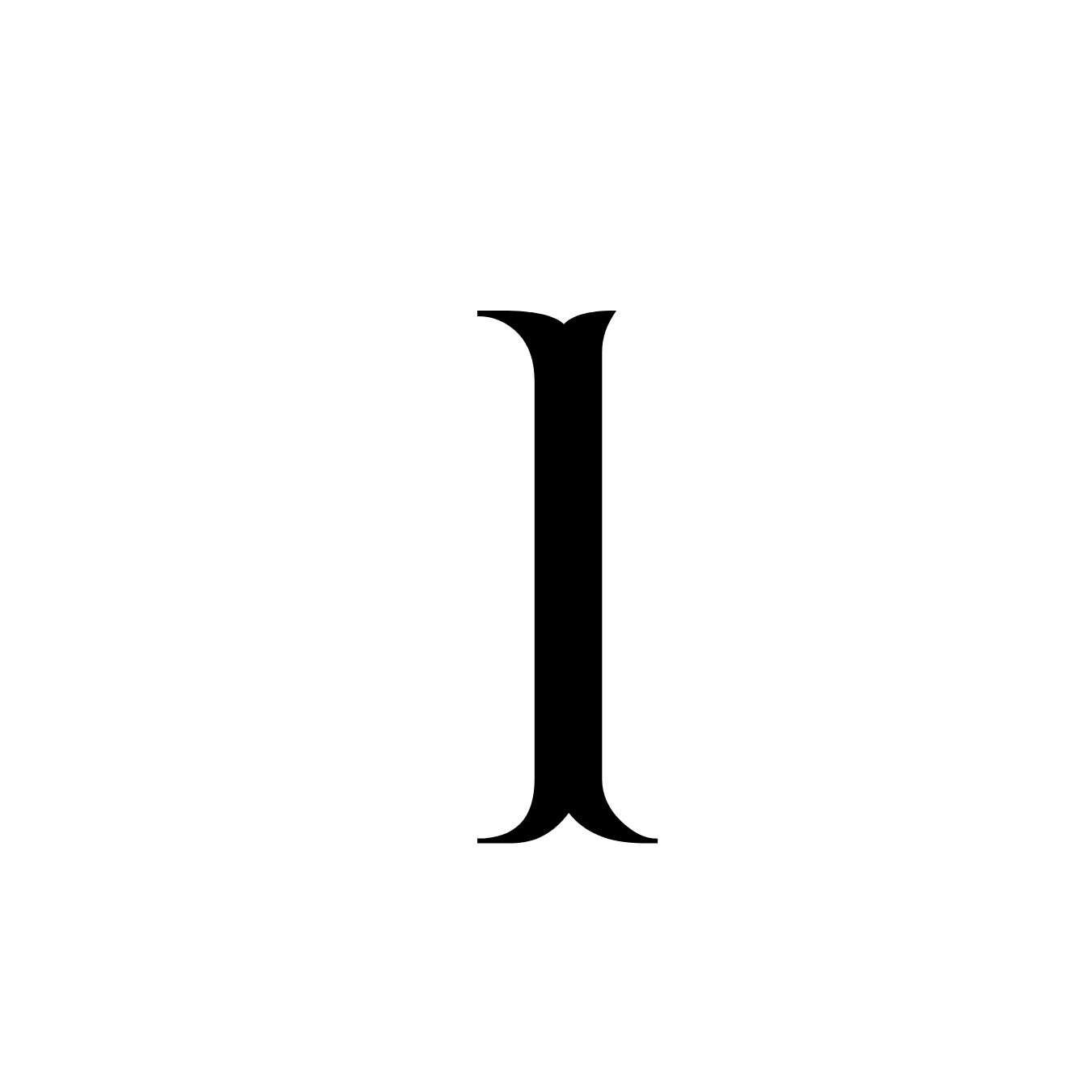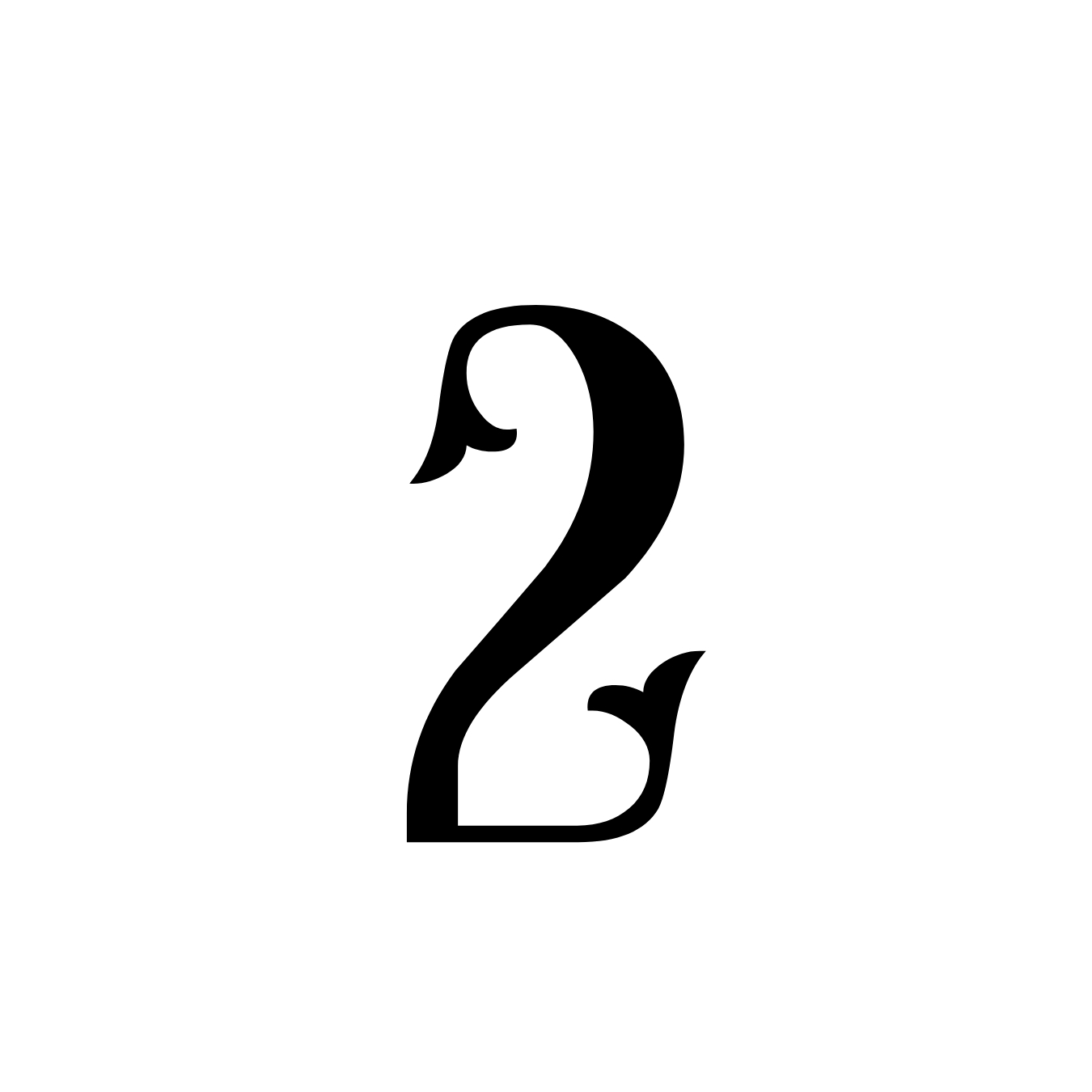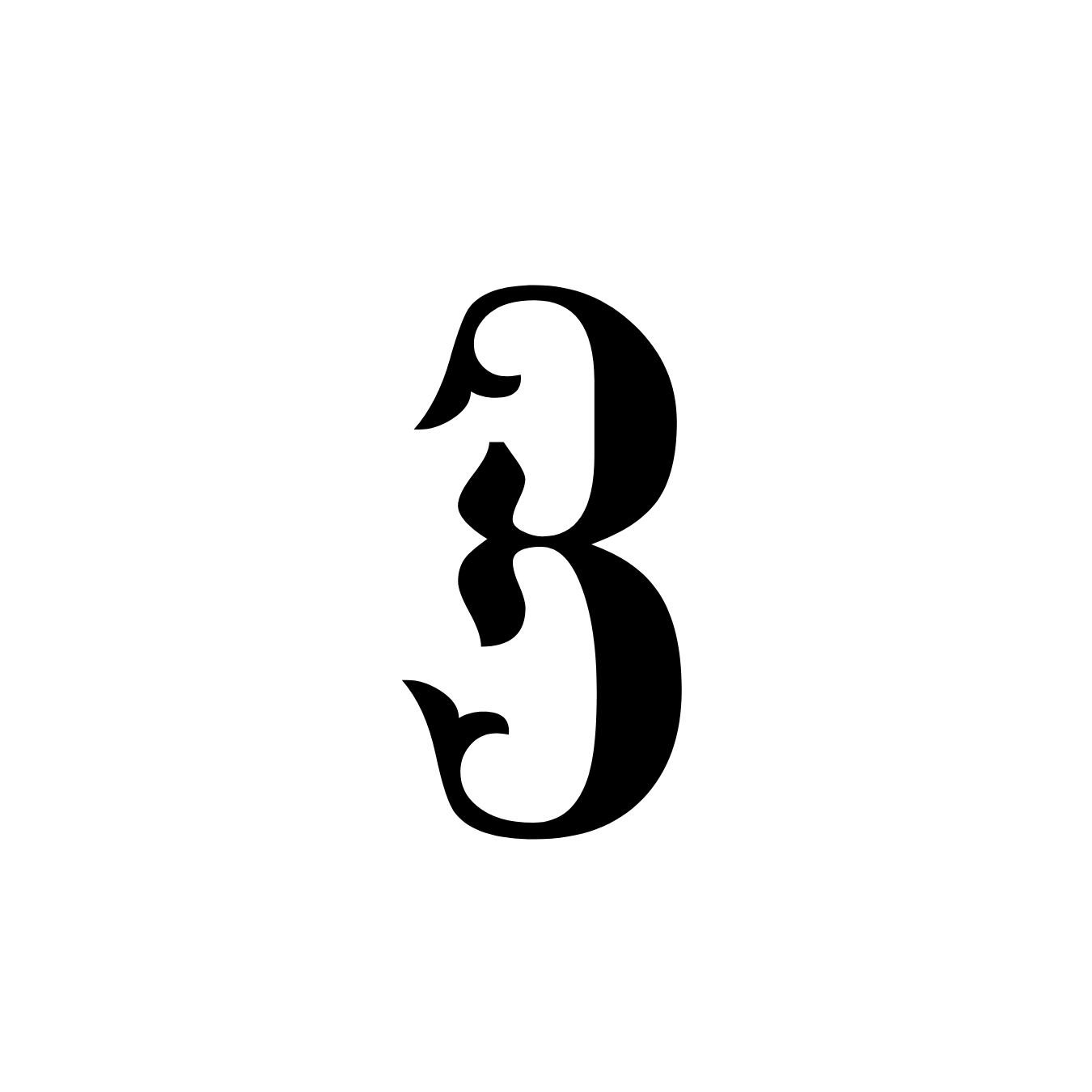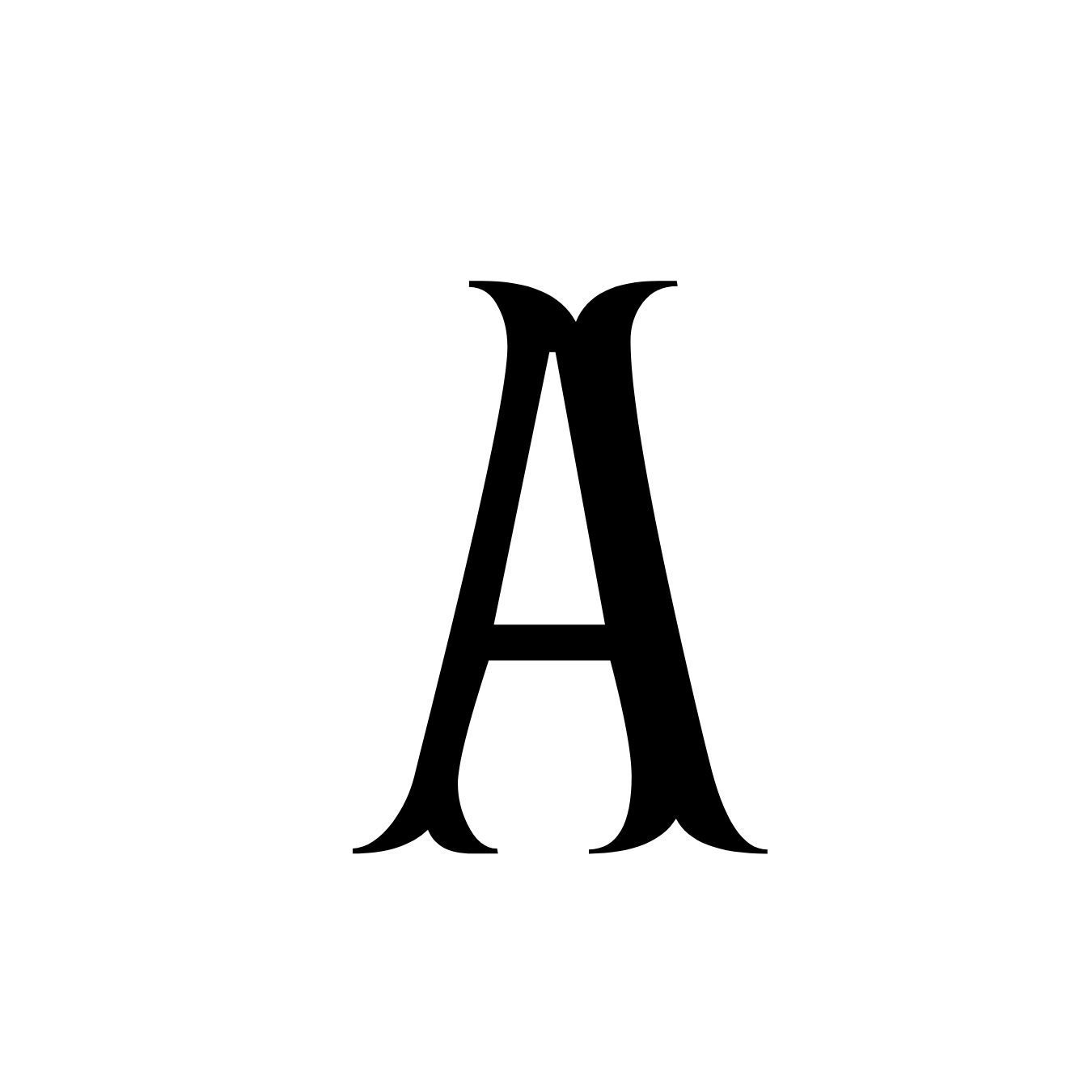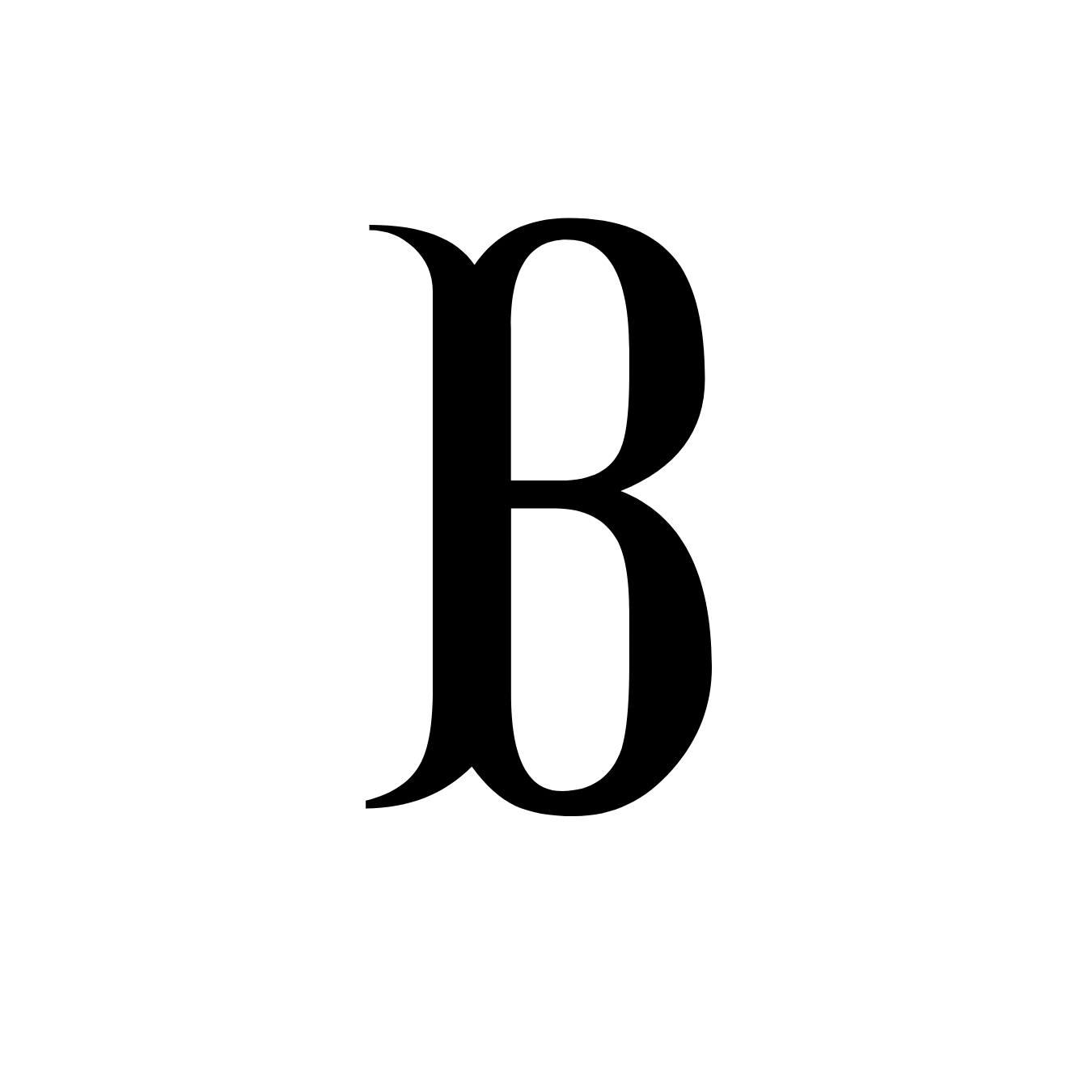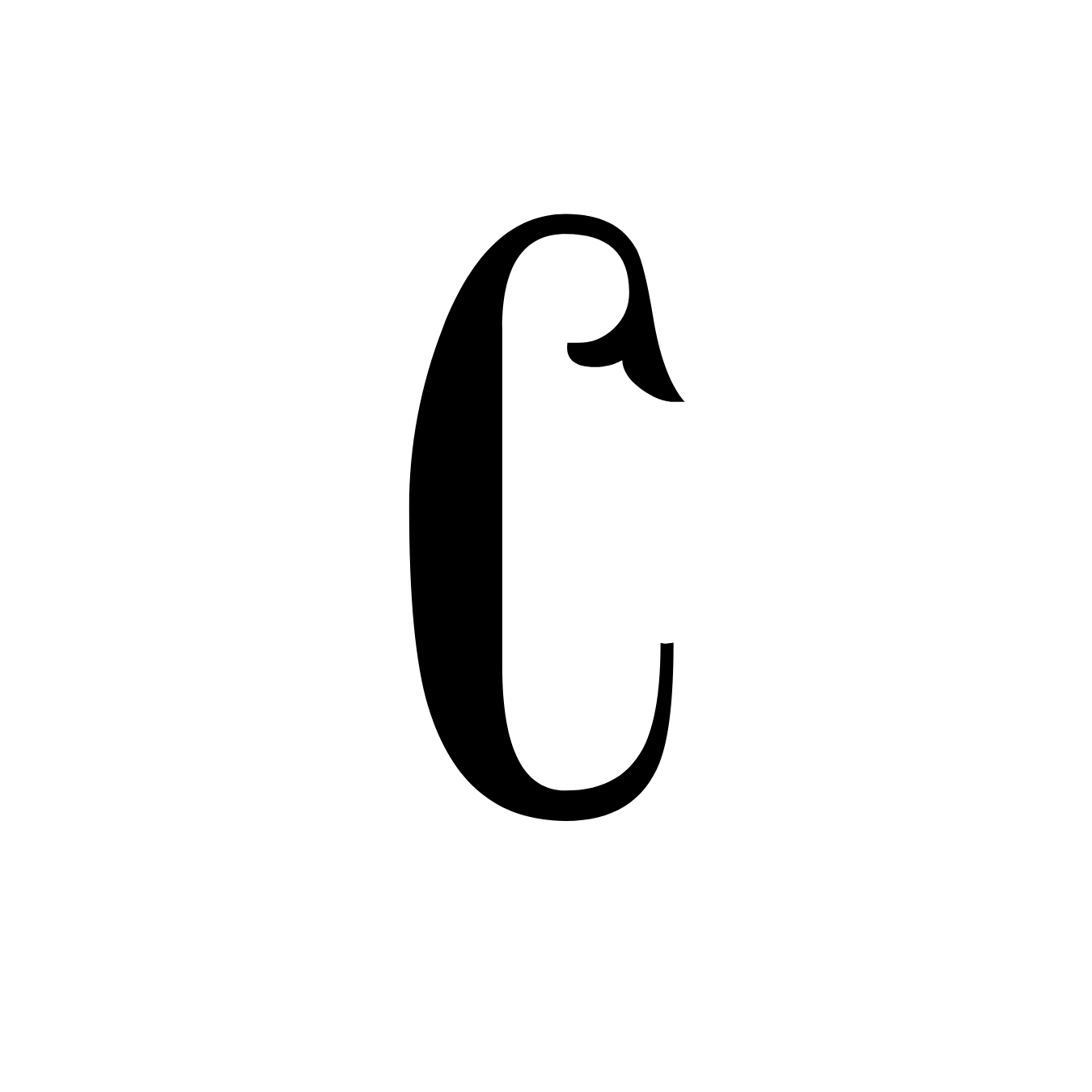
Mermaid Monogramm Schriftart – Dekoratives Alphabet mit Grossbuchstaben, Zahlen und Satzzeichen | Cricut-kompatibel
• Die Mermaid Monogramm Schriftart ist ein dekoratives Display-Alphabet, inspiriert von klassischen Vintage-Schriftstilen mit charakteristischen Fishtail-Endungen. Jeder Buchstabe besitzt gespaltene Spitzen und leicht geschwungene Linien, die den Zeichen eine elegante, ornamentale Optik verleihen. Die Schrift enthält Grossbuchstaben, Zahlen sowie Satzzeichen und bietet damit einen vollständigen Zeichensatz für personalisierte Monogramm-Designs und dekorative Schriftzüge.
• Die Formen sind ausgewogen und klar gestaltet, sodass einzelne Buchstaben besonders gut als Initialen oder zentrale Monogramm-Elemente wirken. Die typischen Fishtail-Endungen verleihen der Schrift einen dekorativen Charakter, ohne die Lesbarkeit zu beeinträchtigen. Dadurch entsteht ein Stil, der zugleich auffällig und strukturiert wirkt.
• Diese Monogramm-Schrift eignet sich für viele kreative Anwendungen wie personalisierte Namen, dekorative Initialen, Etiketten, Geschenkartikel und individuelle Bastelprojekte. Der vom Vintage-Stil inspirierte Look verleiht Designs eine besondere Ausstrahlung, während die Schrift klar und optisch ausgewogen bleibt.